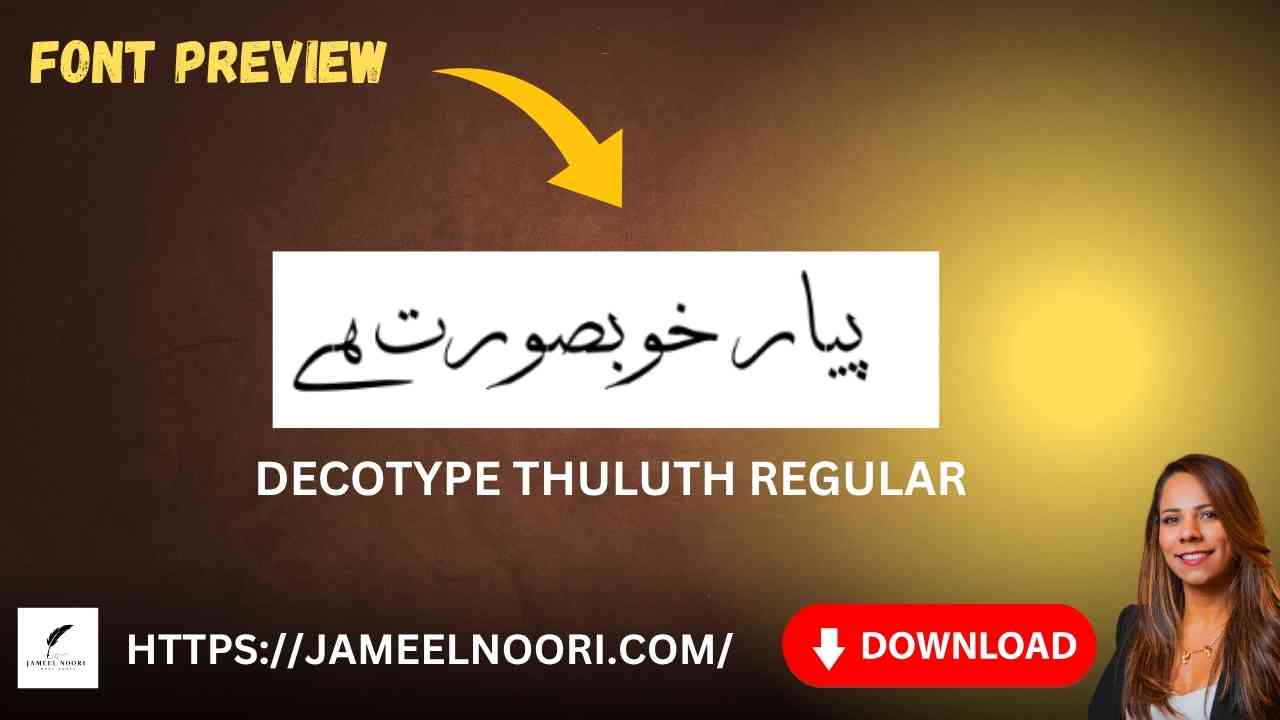
Introduction – Download Urdu font DecoType Thuluth Regular
Agar aap ek professional Urdu font ki talaash mein hain jo design aur readability dono mein best ho, to Download Urdu font DecoType Thuluth Regular aap ke liye best choice ho sakta hai. Ye font specially calligraphic aur traditional style ke shaukeen logon ke liye design kiya gaya hai. Iska use Pakistan ke kai designers aur Urdu content creators kar rahe hain.
Overview of DecoType Thuluth Regular Font
Download Urdu font DecoType Thuluth Regular aik mashhoor aur highly rated TrueType font hai jo Urdu aur Arabic calligraphy ka classical touch deta hai. Is font ka design traditional Thuluth style per mabni hai jo historically Islamic calligraphy mein use hota raha hai.
Why Download Urdu font DecoType Thuluth Regular for Urdu Projects
Aaj kal jab visual identity important ho gayi hai, aesa font jo classical bhi ho aur readable bhi, wohi real game changer banta hai. Download Urdu font DecoType Thuluth Regular isi wajah se designers aur students ke darmiyan kaafi popular ho gaya hai.
Key Benefits:
- Bohat hi elegant aur professional look.
- Urdu books, posters, aur social media ke liye best.
Conclusion: Why You Should Download Urdu font DecoType Thuluth Regular Today
Agar aap Urdu writing ko aik elegant aur classical touch dena chahte hain, to Download Urdu font DecoType Thuluth Regular zarur try karein. Ye aik professional aur trusted font hai jo design, readability aur calligraphy lovers ke liye perfect combo hai. Aaj hi download karein aur apne Urdu content ko next level par le jayein.